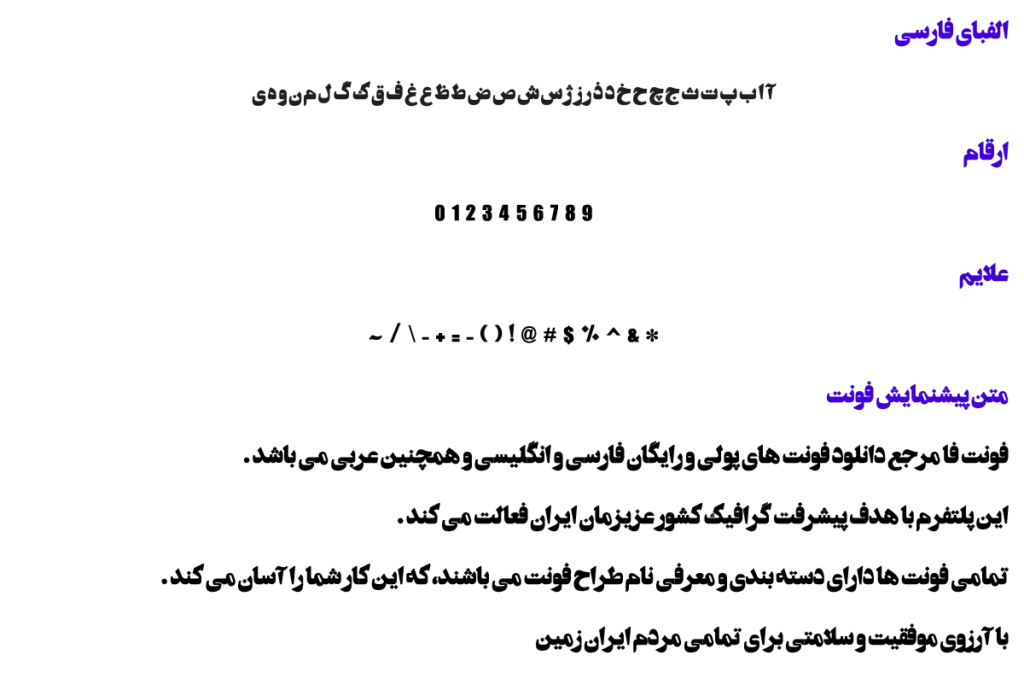
فونت فارسی اردیبهشت – Ordibehesht
سال ساخت فونت: 1394
طراح فونت: حمید قربانپور نوع فونت: فونت عنوان
توضیحات و معرفی فونت اردیبهشت
فونت فارسی اردیبهشت ( Ordibehesht ) از مجموعه فونت های آزاد می باشد، همچنین نوع فونت عنوان می باشد.
فونت فوق العاده زیبای معرفی شده توسط حمید قربانپور با همکاری جعفرپیشه در سال 1394 طراحی و ساخته شده است.
می توان به تایپوگرافی و حروف زینتی مثل ی کشیده اشاره کرد.
همچنین فونت Ordibehesht در یک وزن سنگین است.
ویژگی های فونت زیبای اردیبهشت:
- پشتیبانی کامل از زبان های فارسی، عربی و انگلیسی
- فرم های متنوع برای هر حرف با گلیف های متعدد
- پشتیبانی از لیگچرهای خوشنویسانه
- صدها کرنینگ فشرده برای زیبایی بیشتر
- قابلیت اسکریپت نویسی پیشرفته
- جانمایی دقیق اعراب برای هر حرف
- نمایش ویژه عبارات دینی مانند «علیه السلام» و «صلی الله علیه و آله و سلم»
- و امکانات بیشتر برای یک تایپوگرافی حرفه ای
در تصویر زیر می توانید پیشنمایشی از این تایپ فیس واقعا زیبا رو تماشا کنید…